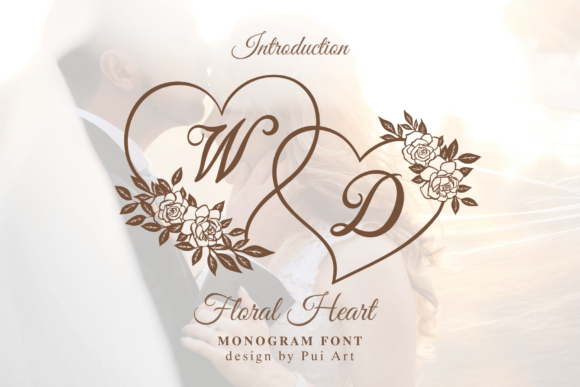
Floral Heart Monogram
適切なデザイン要素を見つけるのは難しい場合がありますが、Floral Heart Monogramは作品を即座に引き立てる優れたコレクションを提供します。
POD(オンデマンド印刷)製品、結婚式の招待状、またはソーシャルメディアのグラフィックを作成している場合でも、Floral Heart Monogramは理想的です。